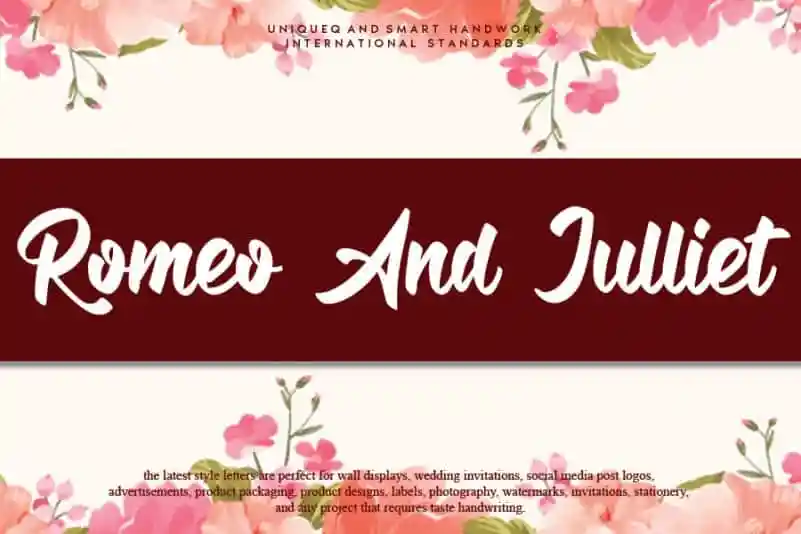
Romeo And Julliet Script Font – Download Grátis
A fonte ‘Romeo And Juliet Script’ é uma escolha perfeita para quem procura uma escrita quase autêntica, que parece ter sido feita à mão por um artesão amante do detalhe. Ela traz o charme e a elegância de um romance clássico ao mesmo tempo em que oferece uma expressividade que se adapta perfeitamente para várias necessidades de design. Ideal tanto para casamentos como cartas de agradecimento, citações ou cartões de agradecimentos, a ‘Romeo And Juliet Script’ também brilha no design de logotipos e cards de business. Suas linhas fluidas e delicadas permitem que você transborde em personalidade com uma escrita elegante e sofisticada sem deixar de capturar o instante mágico da inspiração. Para designers gráficos, a ‘Romeo And Juliet Script’ é um atalho direto para um design autêntico e encantador. Ela combina perfeitamente com qualquer estilo que você decida adotar, desde os mais tradicionais até aqueles mais modernos. Seja qual for o projeto de design em sua mesa, este encantador fonte criará uma atmosfera especial e enriquecerá seu trabalho com um toque autêntico e agradável.